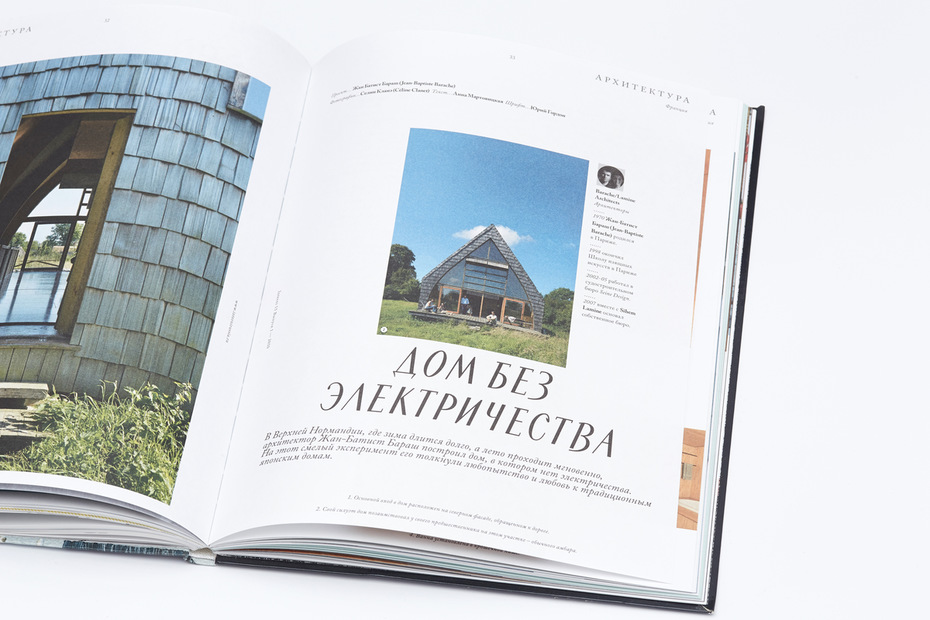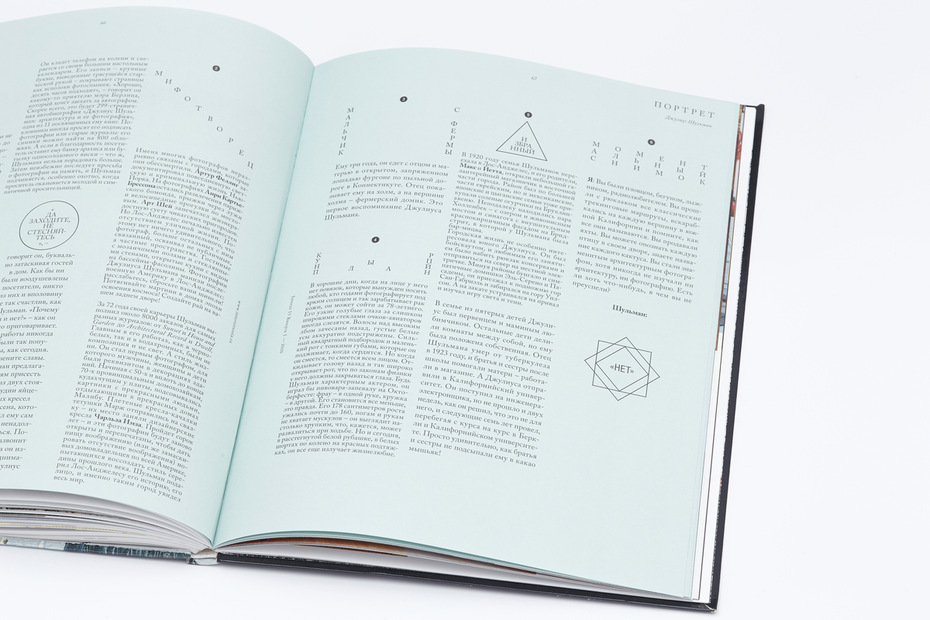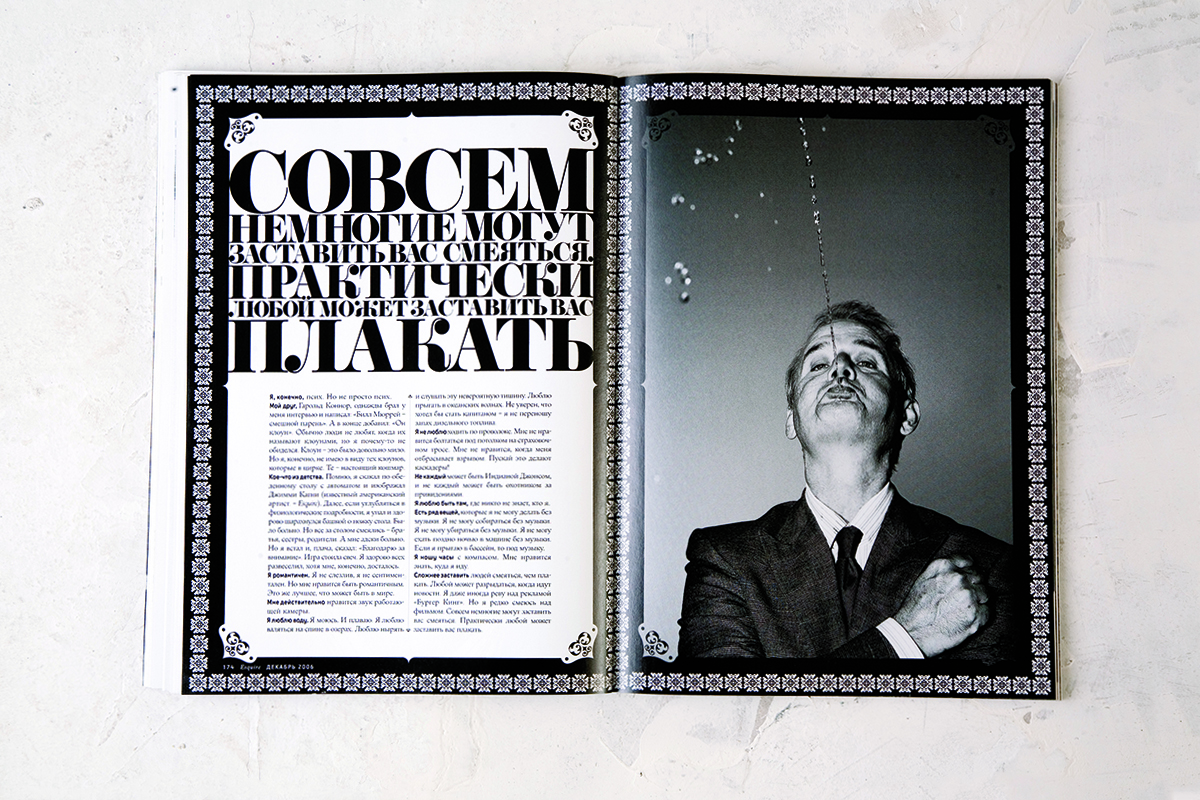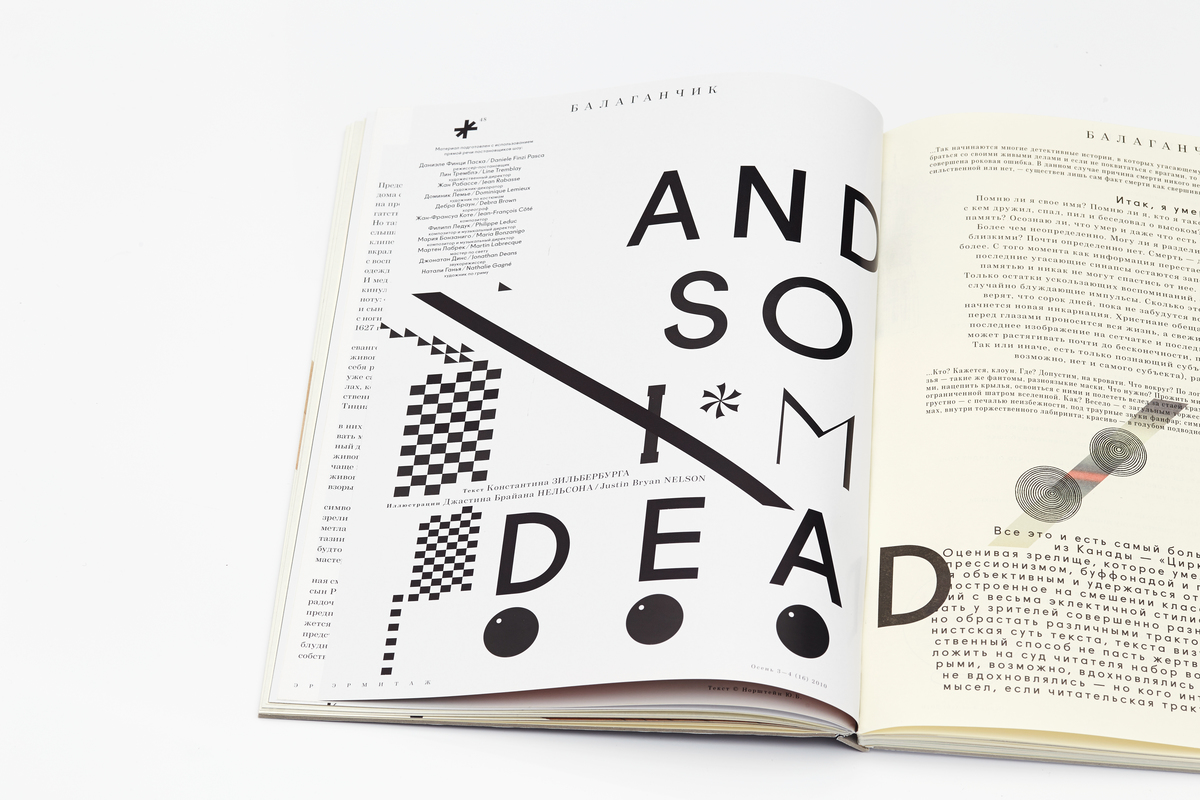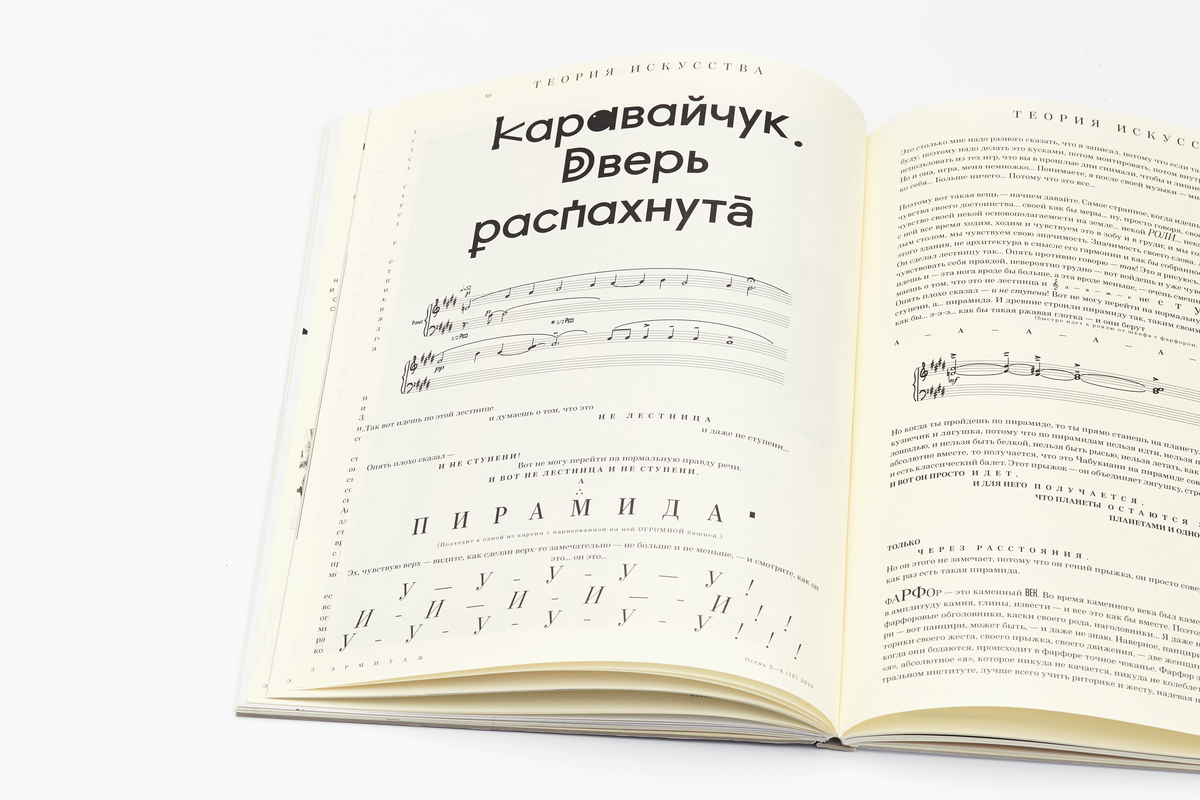
Ди­ма Бар­ба­нель на­хо­дит­ся в Со­чи на бал­ко­не квар­ти­ры, сня­той как лет­няя ре­зи­ден­ция в от­но­си­тель­ной без­опас­но­сти от COVID-19. Ев­ге­ний Юке­чев бе­се­ду­ет из рай­о­на Пан­ков в Бер­ли­не. Ди­му сле­пит май­ское солн­це, а уй­ти с бал­ко­на он не мо­жет — у Юке­че­ва есть же­ла­ние за­дать за­го­тов­лен­ные во­про­сы. Из­на­чаль­ной за­да­чей бы­ло об­су­жде­ние кон­крет­ных про­ек­тов с рас­став­ле­ни­ем по хо­ду нуж­ных ак­цен­тов, но Ди­ма ушёл в ме­та­фи­зи­ку с эле­мен­та­ми ис­по­ве­ди, при­шлось до­пи­сы­вать в два приёма. Уда­лось по­го­во­рить о сле­ду­ю­щем: как раз­ви­вал­ся ме­ди­а­ры­нок в кон­це 90-х и в 2000-е, по­че­му шриф­то­вое пи­рат­ство бы­ло не­из­беж­но­стью для ма­кет­чи­ка, как най­ти ба­ланс меж­ду за­ка­зом и вы­руч­кой и как со­брать во­круг се­бя сот­ни ди­зай­не­ров на еже­днев­ные ди­зайн-тре­ни­ров­ки.
Ди­ма, рас­ска­жи про са­мое на­ча­ло: про ли­хие 90-е, про за­пуск Esquire, про «Афи­шу» и про твои пер­вые ко­ман­ды. Ты ведь вы­рос в ре­дак­ци­ях, пер­вый опыт, на­сколь­ко я по­ни­маю, имен­но жур­наль­ный?
На­вер­ное, на­чать мож­но с «Афи­ши», она бы­ла той точ­кой, ко­гда мы, по­зна­ко­мив­шись с ­Фи­лип­пом Бах­ти­ным, ре­ши­ли ид­ти про­тив те­че­ния. Это был 2001 год, жур­нал «Боль­шой  Го­род». Мы хо­те­ли де­лать со­вер­шен­но но­вую шту­ку, ко­то­рая за­хва­ти­ла бы всё: бы­ла чи­та­е­ма, ­по­пу­ляр­на, ци­ти­ру­е­ма. Мы хо­те­ли, что­бы каж­дая со­ба­ка нас чи­та­ла! Во­об­ще, вся осталь­ная жизнь меж­ду «Афи­шей» и Esquire бы­ла ка­кой-то хал­ту­рой. К при­ме­ру, был кор­по­ра­тив­ный жур­нал, ку­да ме­ня по­звал Да­ни­ла Шо­рох, с ко­то­рым мы то­же ­ра­бо­та­ли в «­Афи­ше» и ко­то­рый пришёл из Playboy так же, как я, толь­ко на год или два поз­же. До это­го я ещё пе­ре­де­лал Playboy в на­уч­но-по­пу­ляр­ный жур­нал из до­воль­но мерз­ко­го из­да­ния о сись­ках. Это из­ба­ви­ло ме­ня от не­об­хо­ди­мо­сти еже­не­дель­но­го ка­стин­га ка­ких-то жен­щин, но при этом я дал чи­та­те­лям воз­мож­ность чи­тать тек­сты, ко­то­рые го­то­ви­ли пре­крас­ные жур­на­ли­сты: ­Ан­тон Кра­сов­ский, Эдик До­рож­кин, Лев Да­нил­кин, Серёжа Ти­тов и мно­го лю­дей, ко­то­рые оста­ви­ли след в жур­на­ли­сти­ке на­ча­ла 2000-х. Од­ним сло­вом, мы на­ча­ли про­цесс раз­ру­ше­ния Playboy как ин­сти­ту­ции и пе­ре­де­ла­ли его в ­ли­те­ра­тур­но-пуб­ли­ци­сти­че­ский дай­джест.
В 2002-м, уво­лив­шись из «Афи­ши» по­сле про­ва­ла пер­вой ите­ра­ции «Боль­шо­го Го­ро­да», мы по­шли с Да­нил­ки­ным де­лать не­мец­кий жур­нал Fit For Fun!, то­же пы­та­ясь пе­ре­де­лать его из де­биль­но­го жур­на­ла во что-то эко­ло­гич­ное.
С че­го на­ча­лась ис­то­рия Esquire в Рос­сии, что ста­ло триг­ге­ром?
В 2004-м Фи­ля [Бах­тин] по­звал ме­ня в жур­нал FHM, на ко­то­рый то­гда ку­пил ли­цен­зию из­да­тель Ми­ха­ил фон Шлип­пе. На са­мом де­ле фон Шлип­пе — это че­ло­век, ко­то­рый ока­зал на ме­ня огром­ное вли­я­ние, да­вая мне дра­го­цен­ную воз­мож­ность де­лать то, что я счи­тал нуж­ным.
Фи­ля ушёл из «Афи­ши», стал гла­варём, со­брал се­бе ко­ман­ду из мод­ни­ков и кра­са­виц. В ка­кой-то мо­мент он ме­ня по­звал на раз­го­вор вме­сте со Шлип­пе. Это был за­жи­га­тель­ный раз­го­вор. Я так, как сей­час, не умел раз­го­ва­ри­вать, я был груст­ный чу­вак, по­то­му что у ме­ня был хро­ни­че­ский га­стрит и я де­лал ве­щи, ко­то­рые мне не нра­ви­лись, и ни­ка­кие бла­га не мог­ли ском­пен­си­ро­вать это ужас­ное ду­шев­ное не­спо­кой­ствие. Раз­го­вор был о том, что «а да­вай-­ка де­лать на­ко­нец то, что мы ре­ши­ли де­лать в ­Афи­ше». То есть да­вай вме­сте сде­ла­ем офи­ген­ную шту­ку, ко­то­рую все бу­дут чи­тать. Это бы­ло на­ча­лом рус­ско­го Esquire. Если бы я ещё чуть-чуть на­хо­дил­ся в том со­сто­я­нии ду­шев­но­го упад­ка, то со мной точ­но бы что-то слу­чи­лось. За эту встре­чу, про­дол­жав­шу­ю­ся ми­нут со­рок, Фи­ля ма­стер­ски, точ­но, вы­ра­зи­тель­но, ве­се­ло сфор­му­ли­ро­вал про­грам­му на сле­ду­ю­щие пять лет. Это бы­ло очень кру­то. Я сра­зу со­гла­сил­ся.
Че­рез ка­кое-то вре­мя я при­е­хал в Independent Media, по­лу­чил там про­стран­ство для пе­ре­го­во­ров и при­ду­мы­ва­ния, и уже в де­ка­бре ­2004-го мы пе­ре­се­ли на Твер­скую в спе­ци­аль­но сня­тый для Esquire офис, и я за­нял­ся най­мом ди­зай­нер­ской ча­сти ко­ман­ды. С Esquire бы­ло всё слож­но, по­то­му что в ка­кой-то мо­мент на­ша друж­ба с Фи­лей раз­ва­ли­лась. Мы бы­ли вы­ну­жде­ны ра­бо­тать вме­сте, но бо­лее ком­форт­ная ра­бо­та бы­ла у Фи­ли с Мак­сом Ни­ка­но­ро­вым, по­то­му что Макс — мяг­кий, тон­ко чув­ству­ю­щий па­рень, не экс­тре­мист.
Мы с Фи­лип­пом хо­те­ли де­лать вы­ра­зи­тель­ные ве­щи на гра­ни до­пу­сти­мо­го, в том чис­ле и для нас са­мих, кван­то­вы­ми прыж­ка­ми пре­одо­ле­вая один свой ком­плекс за дру­гим. Од­на­ко нам обо­им бы­стро ста­ло яс­но, что при об­щей це­ли путь к ней каж­до­му из нас пред­став­лял­ся по-раз­но­му. Где-то Фи­ля был на­мно­го резвее ме­ня — воз­мож­но, я про­сто не по­спе­вал за хо­дом его мыс­ли.
В ито­ге я сде­лал 20 но­ме­ров, это где-то два го­да с хво­стом, хо­тя у ме­ня та­кое впе­чат­ле­ние, что я си­дел в Esquire це­лую веч­ность. Про­сто в ка­кой-то мо­мент ста­ло яс­но, что я сде­лал всё, что хо­тел. На но­вый язык у ме­ня не бы­ло сил, по­то­му что в это вре­мя уже бы­ли сплош­ные скан­да­лы. Фи­ля ушёл из жур­на­ла в 2011-м.
Вы на­ча­ли ра­бо­тать с Юрой Гор­до­ном как раз в Esquire, вер­но? Я по­мню ти­по­гра­фи­че­ские фо­ку­сы в каж­дом но­ме­ре. Это бы­ло, ка­жет­ся, са­мым яр­ким из все­го на рын­ке. Как вы сра­бо­та­лись?
Зна­ешь, я ис­пы­ты­ваю к Юре аб­со­лют­ный пи­е­тет. Мне нра­вит­ся, что он не клас­си­че­ский шриф­то­вик. И я мог с ним раз­го­ва­ри­вать про ве­щи от­влечён­ные, бри­фуя его так же, как я это де­лал со все­ми ху­дож­ни­ка­ми, ил­лю­стра­то­ра­ми, фо­то­гра­фа­ми и т. д. В си­лу соб­ствен­но­го нео­фит­ства я не мог ска­зать: «Про­пор­ции та­кие, за­сеч­ка та­кая, ком­пен­са­ции толь­ко здесь и здесь». Это поз­же я уже смог бри­фо­вать до­ста­точ­но де­таль­но, по­ни­мая осо­бен­но­сти шриф­та. То­гда я ни­че­го про это не знал, мне ну­жен был об­раз. Юра не вда­вал­ся в глу­би­ны про­ек­ти­ро­ва­ния шриф­та, де­лая по­верх­ност­но, но это ме­ня пол­но­стью устра­и­ва­ло. По­то­му что я то­же де­лал сти­ли­сти­че­ское ме­си­во и не стре­мил­ся ни к ка­ко­му вы­хо­ло­щен­но­му чи­сто­плюй­ству — и был по­это­му по­ри­ца­ем все­ми, кем толь­ко мож­но.
Юра — пре­крас­ный ин­стру­мент, он де­лал ров­но то, что нам тре­бо­ва­лось, его луч­шие ре­ли­зы — это всё рав­но ка­кая-то кол­ла­бо­ра­ция, Мак­са с ним или моя с ним.
С са­мо­го на­ча­ла у нас бы­ли шриф­ты из аме­ри­кан­ско­го ма­ке­та — Village и Diadema Фре­де­ри­ка Гау­ди, мы их толь­ко ки­рил­ли­зо­ва­ли, и ещё не­сколь­ко кре­тин­ских шриф­тов ка­ко­го-то гол­ланд­ца, ко­то­рый сде­лал очень стран­ный гро­теск. Мы оста­ви­ли их шриф­ты на пер­вое вре­мя — хо­тя по­том вы­яс­ни­лось, что по ли­цен­зии это­го не тре­бо­ва­лось, но пол­но­стью пе­ре­де­ла­ли весь ма­кет, ни­че­го не взяв из аме­ри­кан­ско­го жур­на­ла, кро­ме ча­сти шриф­тов, на­зва­ния и ло­го­ти­па.
Жур­нал «Эс­квайр», № 5. Глав­ный ре­дак­тор: Фи­липп Бах­тин; арт-ди­рек­тор: Ди­ма Бар­ба­нель.
Фо­то: Ма­ри­ан­на Ро­зен­стил. Ок­тябрь, 2005.
Как «Эс­квайр» по­ле­тел?
Это про­изо­шло уже в на­ча­ле 2005-го. Четвёр­тый но­мер Esquire был для нас всех клю­че­вой, пе­ре­лом­ный. Это тот са­мый но­мер, на об­лож­ке ­ко­то­ро­го Джон Мал­ко­вич с прон­зи­тель­ным взгля­дом. Кста­ти, ма­ло кто за­ме­тил, что в углу гла­за у Мал­ко­ви­ча сле­за . Мы сра­зу по­ня­ли, что де­ло по­шло, ко­гда нам ста­ли да­вать ре­кла­му. Если три пер­вых но­ме­ра мы жи­ли как бы в кре­дит, то даль­ше по­шли про­да­жи, и про­да­жи, нуж­но при­знать, при­лич­ные и да­же уди­ви­тель­ные. Ко­неч­но, это нас очень ра­до­ва­ло. По­хо­же, то, что мы с Фи­лей об­су­жда­ли в 2001 го­ду на бал­ко­не, замёрз­ши­ми паль­ца­ми ки­дая снеж­ки на кры­шу ре­сто­ра­на «Пуш­кин» и на подъ­ез­жа­ю­щие ли­му­зи­ны, ста­ло ре­аль­но­стью. ­Не­ве­ро­ят­ное чув­ство.
Что бы­ло по­сле Esquire? Рас­ска­жешь про Interni? Это же бы­ла аб­со­лют­но эстет­ская ис­то­рия. Уди­ви­­тель­но, что он ­про­дер­жал­ся так дол­го.
Жур­нал Interni по ре­дак­тор­ской и мар­ке­тин­го­вой за­дум­ке со­сто­ял из двух ча­стей. Мы не хо­те­ли ста­вить ре­кла­му во вто­рую часть жур­на­ла прин­ци­пи­аль­но, она со­сто­я­ла сплошь из ре­дак­ци­он­но­го кон­тен­та, со­бран­но­го на мод­няц­кой рых­лой бу­ма­ге. Ита­льян­ский Interni был кон­сер­ва­ти­вен, мы за­да­ли тренд, ко­то­рый под­хва­ти­ло ещё не­сколь­ко ли­цен­зи­а­тов, а по­том и са­ми ита­льян­цы по­ме­ня­ли ма­кет на чуть бо­лее со­вре­мен­ный, а с ним и де­ле­ние на две ча­сти и раз­ные бу­ма­ги. Пер­вая часть жур­на­ла бы­ла на глян­це­вой ме­лов­ке, бе­лиз­на бы­ла не­силь­ная. Все руб­ри­ки бы­ли при­ду­ма­ны та­ким об­ра­зом, что­бы уме­щать­ся в по­ло­су или мак­си­мум в две. Ред­кол­ле­гия, со­би­рав­ша­я­ся на че­ты­ре ча­са раз в не­де­лю, да­ва­ла воз­мож­ность всей ко­ман­де пол­но­стью уви­деть про­дукт и по­том в те­че­ние двух не­дель про­из­вод­ства за­ни­мать­ся лишь до­строй­кой, тю­нин­гом. В эти че­ты­ре ча­са всё при­ду­мы­ва­лось с вы­со­чай­шей кон­цен­тра­ци­ей вни­ма­ния и очень точ­ным спар­рин­гом меж­ду участ­ни­ка­ми. Веб толь­ко-толь­ко на­чи­нал­ся, и мы как бы иг­ра­ли в не­го на бу­ма­ге.
Вто­рая часть бы­ла рых­лая и очень сво­бод­ная в пла­не воз­ду­ха, мы ком­по­но­ва­ли как хо­те­ли. Пер­вая ите­ра­ция ма­ке­та (2007 – 2009) бы­ла без сквоз­ной сет­ки. Ко­гда я за­ни­мал­ся пе­ре­дел­кой Harper’s Bazaar, мне уда­лось про­ме­рить но­ме­ра 60-х го­дов из ар­хи­вов Хёр­ста , и я по­нял, что ста­ри­ки-ма­кет­чи­ки ис­поль­зо­ва­ли ка­кую-то сквоз­ную си­сте­му, ко­то­рую я дол­го ис­кал. Я хо­тел най­ти ре­ше­ние — и нашёл. Я на­звал этот спо­соб сквоз­ной сет­кой и на­чал его сра­зу же при­ме­нять.
До Esquire, в Playboy, я ду­мал, что всё стро­ит­ся на це­лых чис­лах, что мне нуж­но всё счи­тать в мет­ри­че­ских чис­лах. Ко­гда же я стал де­лать ма­ке­ты толь­ко в пунк­тах, то со­кра­тил по­греш­ность сра­зу очень силь­но. Всё на­ча­ло схо­дить­ся иде­аль­но, я кай­фо­вал от ощу­ще­ния, что по­ми­мо класс­ных ре­ше­ний у нас класс­ные тек­сты ино­гда и класс­ные кар­тин­ки. Луч­шие ав­то­ры хо­тят с на­ми ра­бо­тать. При этом, если кто-ли­бо придёт и ска­жет: «Так, что это за ха­ос?», я его в по­ро­шок со­тру. Я мо­гу на­гляд­но до­ка­зать, что в стра­не так ни­кто не де­ла­ет. Это бы­ло до­стиг­ну­то про­сто ко­ли­че­ством ча­сов. Я обыч­ный че­ло­век. В моём слу­чае вы­иг­ры­ва­ют хо­ро­ши­сты, а не ге­нии: они ко­вы­ря­ют, ко­вы­ря­ют и на­хо­дят. И я нашёл кое-что, что даёт мне по­ни­ма­ние па­ра­мет­рии и про­пор­ци­о­ни­ро­ва­ния, ме­то­дов ком­по­зи­ции. Interni — пер­вый жур­нал, ко­то­рый был сде­лан тех­но­ло­ги­че­ски ­ка­че­ствен­но.
По­го­во­рим о прак­ти­ке вза­и­мо­дей­ствия вну­три ди­зайн-ко­ман­ды? Как те­бе удаёт­ся во­вле­кать в ра­бо­ту и точ­ным об­ра­зом на­стра­и­вать участ­ни­ков про­цес­са?
У ме­ня есть пред­став­ле­ние о не­ко­ей иде­аль­ной ра­бо­чей мо­де­ли. Это имен­но мо­дель, поз­во­ля­ю­щая пра­виль­но по­до­бран­ным лю­дям с пра­виль­ны­ми ком­пе­тен­ци­я­ми, до­кру­чен­ны­ми в ре­зуль­та­те сов­мест­ной ра­бо­ты, на ред­кол­ле­гии иметь силь­ную и точ­ную со­на­строй­ку меж­ду участ­ни­ка­ми. Со­на­строй­ка поз­во­ля­ла до­стичь глу­бин­ных, до слёз, ин­сай­тов, ко­то­рые ка­са­лись точ­но­сти, бли­зо­сти об­ра­за и смыс­ла, их сты­ков­ки. Меж­ду ре­дак­то­ром и ди­зай­не­ром про­ис­хо­ди­ло глу­бин­ное ду­хов­ное со­при­кос­но­ве­ние, со­еди­не­ние в еди­ную це­лост­ную ра­бо­чую еди­ни­цу.
Даль­ше очень важ­ную роль иг­ра­ет бриф. Моя ме­то­ди­ка со­став­ле­ния бри­фа поз­во­ля­ет вы­бран­но­му че­ло­ве­ку, ис­хо­дя из по­ни­ма­ния мной его точ­ки стар­та, его про­фес­си­о­наль­но­го и ду­хов­но­го век­то­ра, пред­ло­жить имен­но то, что даст ему мас­шта­би­ро­вать­ся че­рез мою при­клад­ную за­да­чу. Я опи­ра­юсь на глу­бо­кое зна­ние че­ло­ве­ка и его ги­по­те­ти­че­ских воз­мож­но­стей, ко­то­рые при опре­делён­ных, очень чёт­ко сфор­му­ли­ро­ван­ных усло­ви­ях да­дут ему ре­а­ли­зо­вать­ся и рас­крыть­ся.
Ре­а­ли­за­ция по­тен­ци­а­ла — это во­об­ще са­мая важ­ная шту­ка, поз­во­ля­ю­щая де­лать не­обык­но­вен­ные ве­щи и очень бы­стро да­ю­щая рост лю­дям, ко­то­рые за­ча­стую не по­ни­ма­ют и не зна­ют, но бес­со­зна­тель­но жа­ждут соб­ствен­но­го раз­ви­тия. Они ищут, они му­ча­ют­ся из-за не­вы­ска­зан­но­сти, и ты им даёшь то, что при­но­сит им мг­но­вен­ный, ча­сто очень бо­лез­нен­ный, но не­обык­но­вен­ный рост.
Я до­пус­каю: то, что они сде­ла­ют, бу­дет не тем, что я хо­тел и про­сил, со­вер­шен­но дру­гим. Но я мо­гу это адап­ти­ро­вать. Вся осталь­ная моя си­сте­ма — ма­кет, ти­по­гра­фи­ка, струк­ту­ра свя­зей — она управ­ля­е­ма, я мо­гу её под­стро­ить так, что­бы эти ве­щи — жи­вые, жиз­нен­ные, ис­крен­ние и точ­ные — при­ня­ли но­вое ре­ше­ние. Я го­во­рю: «Это офи­ген­но! Не со­всем то, но это кру­то. Я сде­лаю свою часть по-дру­го­му, хо­па!»
Ты по­стро­ил Campus  для ди­зай­не­ров на тер­ри­то­рии сво­е­го до­ма и за­пу­стил тре­ни­ров­ки Designworkout. Что даёт это те­бе в дол­го­сроч­ной пер­спек­ти­ве?
Это во­об­ще чу­до. Уди­ви­тель­но, что это про­изо­шло и ста­ло ре­аль­но­стью. Без «Ян­дек­са» и без Ильи Се­га­ло­ви­ча ни­че­го бы не по­лу­чи­лось. Он по­че­му-то по­ве­рил в нас и про­фи­нан­си­ро­вал стро­и­тель­ство и пер­вые два го­да ра­бо­ты. Сту­ден­ты там за­ни­ма­лись аб­со­лют­но бес­плат­но, про­жи­вая в Кам­пу­се по пять не­дель, имея воз­мож­ность за­ни­мать­ся с уди­ви­тель­ны­ми, очень та­лантли­вы­ми ма­сте­ра­ми.
Се­го­дня прин­цип от­бо­ра на вор­ка­ут до­воль­но жёст­кий. Сю­да по­па­да­ют те, кто при­сы­ла­ет ра­бо­ту во­вре­мя каж­дый день, де­ла­ет её вы­ра­зи­тель­но и очень ка­че­ствен­но. Да­же пя­ти­ми­нут­ная по­да­ча долж­на быть сде­ла­на фан­та­сти­че­ски ка­че­ствен­но. Если че­ло­век не по­ни­ма­ет эту ме­ру ка­че­ства, то на­учить его ск­ла­ды­вать руч­ки по ро­сту и ка­ран­да­ши по мяг­ко­сти, иметь чи­стую кла­ви­а­ту­ру и вы­ров­нен­ную стоп­ку бу­маг не­воз­мож­но — это куль­ту­ра вза­и­мо­дей­ствия с про­стран­ством.
Я вы­би­раю тех, кто не про­сто го­рит или дёр­га­ет ме­ня за ру­кав, а тех, кто бу­дет си­деть пять но­чей под­ряд, всё рав­но сде­ла­ет гов­но, но бу­дет си­деть и ка­кая-то ис­кра у не­го прой­дёт. Я уви­жу, где она! Это один из сот­ни или ты­ся­чи, но они при­хо­дят, и сла­ва бо­гу.
Прак­ти­ка у Бар­ба­не­ля для мно­гих ди­зай­не­ров по­слу­жи­ла силь­ным толч­ком к про­фес­си­о­наль­но­му раз­ви­тию. Как ты это­го до­би­ва­ешь­ся?
Я ду­маю, де­ло в са­мом фор­ма­те мен­тор­ства, или пе­сто­ва­ния, мне нра­вит­ся это ста­ро­рус­ское сло­во. Это сло­во скры­ва­ет один из клю­че­вых фрейм­вор­ков для вза­и­мо­дей­ствия в ко­ман­де, тех­ни­ка на­зы­ва­ет­ся «дед». Она по­хо­жа на от­но­ше­ния двух лю­дей — стар­ше­го и млад­ше­го,— по­стро­ен­ные на ­до­ве­рии.
У от­ца, как пра­ви­ло, нет вре­ме­ни на де­тей, увы. Де­ды же своё от­ра­бо­та­ли, они име­ют ­воз­мож­ность по­свя­тить оста­ток жиз­ни вну­кам. Дед не про­сто жу­чит вну­ка, как это де­ла­ет отец по при­чи­не от­сут­ствия вре­ме­ни. Отец, вме­сто то­го что­бы по­го­во­рить с сы­ном сер­деч­но, в су­е­те осу­жда­ет его за ка­кую-то глу­пость (не вы­мыл го­ло­ву, порвал крос­си­ки, по­те­рял но­вый мяч). Для де­да это чушь, он да­же не за­ме­ча­ет это­го. Де­ду важ­но слы­шать вну­ка, ви­деть но­вую жизнь и по­ни­мать, что он и внук — это ча­сти од­ной ли­нии, точ­ка А и точ­ка Б.
Дед — это тот, кто не бу­дет го­во­рить ни­че­го су­про­тив, ни­как ком­мен­ти­ро­вать и осу­ждать, он лю­бит без­услов­но (если это хо­ро­ший дед), поз­во­ляя вну­ку рас­крыть всю кра­со­ту его сущ­но­сти. Я ск­ло­нен ис­поль­зо­вать эту тех­но­ло­гию для ре­бят. Я ни­где это осо­бо не афи­ши­рую, но я ­по­ни­маю, что это даёт им воз­мож­ность быть спо­кой­ны­ми, что у них за спи­ной есть друг, ко­то­рый их не осу­дит и все­гда под­дер­жит. Это даёт нам кре­пость.
Всё это пред­по­ла­га­ет очень силь­ную фо­ку­си­ров­ку и от­вет­ствен­ность. Для про­ек­ти­ро­ва­ния этот мо­мент — один из са­мых важ­ных. И в нём же под­пунк­том яв­ля­ет­ся не­твор­кинг — как ре­бя­та вза­и­мо­дей­ству­ют друг с дру­гом без ме­ня. Они мо­гут про­ек­ти­ро­вать что-то без ме­ня, на­стра­и­вая соб­ствен­ные рег­ла­мен­ты, и это очень хо­ро­шо.
Но всё же глав­ное для ме­ня — это, ко­неч­но, пе­ре­дать ре­бя­там по­ни­ма­ние, что нуж­но все­гда ра­бо­тать на смысл, важ­но, что­бы бы­ла це­лост­ность про­дук­та и ми­ра во­круг, про­дук­та и то­го, кто им за­ни­ма­ет­ся. Нуж­но, что­бы был слы­шен смысл! И со­вер­шен­но не тот, что со­дер­жит­ся в кли­ент­ском про­дук­те, ко­то­рый я пе­ре­де­лы­ваю, а тот са­мый Боль­шой смысл, сви­де­тель­ству­ю­щий о моём кро­шеч­ном, ми­кро­ско­пи­че­ском, му­сор­ном, без­мозг­лом уров­не, о при­сут­ствии Бо­га во­круг. Всё. Это един­ствен­ная моя цель как в про­ек­ти­ро­ва­нии, так и в мен­тор­ской прак­ти­ке.
Я мо­гу ви­деть це­лост­ность про­дук­та и пе­ре­хо­дить на слои очень бы­стро — это во­прос тре­ни­ров­ки ума. Я мо­гу ре­гу­ли­ро­вать глу­би­ну про­ник­но­ве­ния в об­раз, ско­рость, зу­ми­ро­вать, об­хо­дить, не те­ряя вни­ма­ния и на­хо­дя не­ли­ней­ные свя­зи меж­ду ком­по­нен­та­ми си­сте­мы. Ди­зай­не­ры при­хо­дят, по су­ти, ров­но за этим.
Рас­ска­жи о жур­на­ле «Эр­ми­таж». Я знаю, что это был не­про­стой про­ект. Вы­шло все­го два но­ме­ра, из ко­то­рых удач­ным ты счи­та­ешь толь­ко один. На чём ты стро­ил ма­кет, как те­бе в го­ло­ву при­шли эти ди­кие кон­струк­ции и об­ра­зы?
По­ни­ма­ешь, я ведь не ис­хо­жу из ма­те­ри­а­лов в ма­ке­ти­ро­ва­нии. Я опи­рал­ся на блю­принт, то есть на раз­вёр­ну­тое по­вест­во­ва­ние о струк­ту­ре из­да­ния, вну­трен­них смыс­ло­вых свя­зях меж­ду ком­по­нен­та­ми и о той су­пер­за­да­че, ко­то­рую эти ком­по­нен­ты в каж­дой руб­ри­ке долж­ны вы­пол­нять. Я уви­дел ор­га­низм из­да­ния, ко­то­рый пред­став­лял со­бой про­стран­ство, как буд­то ав­стра­лий­ский скрэб — ты за­хо­дишь и ви­дишь ку­чу ве­ток, эти вет­ки со­еди­не­ны. Ощу­ще­ние, что ты вошёл в очень плот­ную ней­рон­ку. У те­бя ку­ча свя­зей, и ты дол­жен их учи­ты­вать в ма­ке­те та­ким об­ра­зом, что­бы они рас­кры­лись и ин­тер­фейс жур­на­ла был по­ня­тен. UX был все­гда! Про­сто тер­мин стал по­пу­ляр­ным в по­след­ние де­сять лет, а этим все, соб­ствен­но, и за­ни­ма­лись, про­ек­ти­руя.
На про­тя­же­нии всей жиз­ни я тя­ну за од­ни и те же нит­ки. Я их про­сто вы­тя­ги­ваю даль­ше и даль­ше. Кста­ти, че­рез де­сять лет по­сле то­го, как мы сде­ла­ли шрифт для «Эр­ми­та­жа», я по­зво­нил Юре и ска­зал: «Юр, наш за­каз­чик — по­соль­ство Ир­лан­дии, да­вай этот шрифт сда­дим ир­ланд­цам, до­ба­вим ту­да раз­ной жу­ти, ко­то­рая бы иден­ти­фи­ци­ро­ва­лась ими как на­ци­о­наль­ная». На про­тя­же­нии дол­гих лет это од­ни и те же иг­ро­ки, у ко­то­рых жизнь раз­ви­ва­ет­ся бла­го­да­ря про­ек­там.
Со­дер­жа­тель­ная часть «Эр­ми­та­жа» до на­ше­го втор­же­ния в ре­дак­цию бы­ла лю­бо­пыт­ной, а для мно­гих и во­все без­ум­ной, но если коп­нуть глуб­же, на­вер­ное, мне бы­ло скуч­но­ва­то с ни­ми. Я был увлечён, ра­до­вал­ся каж­до­му но­ме­ру, но при этом со­дер­жа­тель­ная и об­раз­ная це­лост­ность впер­вые бы­ла до­стиг­ну­та толь­ко Серёжей Мо­на­хо­вым, мы его при­гла­си­ли ре­дак­то­ром на вто­рой но­мер. Это бы­ла вспыш­ка Серёги­но­го ге­ния. Мне нра­вил­ся его не­ве­ро­ят­ный без­ум­ный ум. Мы бы­ли все на сво­их ме­стах: я не лез, он не лез, мы про­сто со­труд­ни­ча­ли, ду­ма­ли, ужа­са­лись вме­сте. Это был очень глу­бо­кий про­цесс. Но на уров­не ре­ше­ний он был не та­кой кру­той, как смысл. По­ни­ма­ешь, во всех хо­ро­ших ра­бо­тах (а их очень ма­ло) все­гда глав­ную роль иг­ра­ют два об­сто­я­тель­ства, ко­то­рые обес­пе­чи­ва­ют ско­рость и вы­ра­зи­тель­ность,— это, без­услов­но, друж­ба и му­за.
В ма­ке­те «Эр­ми­та­жа» гро­теск Fugue Ра­ди­ма Пеш­ко про­зву­чал до­воль­но гром­ко и вы­шел да­ле­ко за его пре­де­лы, о нём (о вас) го­во­ри­ли мно­го и с эн­ту­зи­аз­мом. Что дал этот шрифт те­бе и ма­ке­ту?
Ма­кет уточ­нял­ся два но­ме­ра, бе­лый был пи­лот­ный, в це­лом не­удач­ный. Де­лая вто­рой но­мер, мы учли всё и сде­ла­ли со­вер­шен­но дру­гой жур­нал. Плюс Ра­дим Пеш­ко анон­си­ро­вал ки­рил­ли­цу Fugue, и не бы­ло ну­жды поль­зо­вать­ся кон­тра­факт­ной — на моём пу­ти к от­ка­зу от пи­рат­ства это бы­ло очень во­вре­мя. По­ня­тия «ма­кет» на са­мом де­ле в жур­на­ле «Эр­ми­таж» не­ту. Там нет ша­бло­нов и ком­по­но­воч­ных схем, в основ­ном про­сто раз­мер­но­сти шриф­тов и от­но­ше­ния эле­мен­тов. Сам ма­кет по­стро­ен на сквоз­ной сет­ке с ша­гом мо­ду­ля 5,834 мм, ко­то­рый яв­ля­ет­ся и меж­ко­лон­ни­ком. Внеш­ние от­сту­пы так­же под­чи­не­ны это­му мо­ду­лю, что даёт об­ра­зу ак­ту­аль­ную для 2010 го­да остро­ту. Этот но­мер там, по-мо­е­му, ни­ко­му не по­нра­вил­ся. Кро­ме Пио­тров­ско­го. Осталь­ные не до­го­ня­ют, ко­му и за­чем всё это нуж­но. Пио­тров­ский, уди­ви­тель­ный че­ло­век, под­пи­сал этот ма­кет в пе­чать. Я бы не под­пи­сал, будь я на его ме­сте.
Мне за­по­мни­лось ин­тер­вью с Оле­гом Ка­ра­вай­чу­ком из вто­ро­го но­ме­ра. Ма­кет и ти­по­гра­фи­ка уди­ви­тель­но точ­но сов­па­да­ют с экс­цен­трич­ной лич­но­стью ком­по­зи­то­ра и его по­вест­во­ва­ни­ем.
Это ве­ли­кий сю­жет! В этом ма­те­ри­а­ле Ка­ра­вай­чук сам вы­сту­пил ти­по­гра­фом, вы­де­лив в вёрст­ке не­об­хо­ди­мые по смыс­лу (и зву­ча­нию) ак­цен­ты и опре­де­лив всю ком­по­зи­цию пуб­ли­ка­ции. Но­мер вы­пус­кал­ся, ко­гда эпо­ха фан­та­зий­ных шриф­тов-ги­бри­дов бы­ла ещё при­зрач­ным бу­ду­щим. На за­ход­ной по­ло­се — по­пыт­ки до­пол­нить кас­су Fugue аль­тер­на­тив­ны­ми зна­ка­ми для под­держ­ки той ди­ко­сти, ко­то­рую Ка­ра­вай­чук устро­ил вну­три. Ва­ри­а­ции тек­сто­вых раз­ме­ров — от 6,3 до 27 пт. Ждан при­ни­мал уча­стие в раз­мет­ке и был в вос­тор­ге от про­цес­са.
Ин­тер­вью с Оле­гом Ка­ра­вай­чу­ком (1927 – 2016) из вто­ро­го но­ме­ра жур­на­ла «Эр­ми­таж».
Ждан Фи­лип­пов, ди­зай­нер, со­труд­ник «Ма­стер­ской» в 2012 – 2015 го­дах: «Ра­бо­та над этой пуб­ли­ка­ци­ей ве­лась сов­мест­но с са­мим Оле­гом. Сто­я­ла за­да­ча со­про­во­дить текст му­зы­каль­ны­ми за­ри­сов­ка­ми, и Ка­ра­вай­чук с го­тов­но­стью пре­па­ри­ро­вал текст, на­ки­ды­вал нот­ные этю­ды, жон­гли­ро­вал строч­ка­ми и вме­сте с ди­зай­не­ром при­ду­мы­вал вы­ра­зи­тель­ные ти­по­гра­фи­че­ские ре­ше­ния для всех раз­во­ро­тов».
Из по­след­них ра­бот был ма­кет жур­на­ла «Ис­кус­ство ки­но»? На­сколь­ко я по­нял, про­ект не при­ня­ли и всё ушло в стол. Вещь мог­ла по­лу­чить­ся со­вре­мен­ная и дерз­кая. Рас­ска­жи по­дроб­нее.
«Ис­кус­ство ки­но» — ле­ген­дар­ный со­вет­ский жур­нал. Он вы­хо­дит с се­ре­ди­ны 20-х го­дов. Идея пе­ре­осмыс­лить и воз­ро­дить об­раз жур­на­ла для ме­ня иде­аль­ная. Я лю­блю ра­бо­тать со старьём, вы­тас­ки­вать из не­го всю си­лу сде­лан­но­го, про­жи­то­го и пе­ре­са­жи­вать это в на­шу ре­аль­ность, в се­го­дняш­нюю зем­лю. По­ни­ма­ешь, это да­же не со­всем про ди­зайн, это про про­дол­же­ние тра­ди­ций, про со­хра­не­ние куль­ту­ры, причём той куль­ту­ры, ко­то­рая да­ла фан­та­сти­че­ские рост­ки. Мне важ­ны зёр­на, я пол­заю по пла­не­те и со­би­раю их как мо­гу. По­это­му для ма­ке­та я на­хо­дил сна­ча­ла ре­фе­рен­сы из 60-х, 70-х, жур­на­лы о ки­но, ис­кус­стве, ко­то­рые де­ла­ли ста­ри­ки.
Про­ве­дя не­боль­шое изыс­ка­ние, я незна­чи­тель­но скор­рек­ти­ро­вал вы­со­ту и ши­ри­ну, вы­сту­пая ско­рее служ­бой са­на­ции, не­же­ли пи­о­не­ром графди­зай­на. Ло­мать ни­че­го не хо­те­лось, но ка­за­лось, что нуж­но уточ­нить: по­след­няя ите­ра­ция ма­ке­та вы­гля­де­ла со­всем слу­чай­ной. Я от­ре­зал ши­ри­ну и до­ба­вил вы­со­ту, по­лу­чи­лась про­пор­ция ки­но­кад­ра — 1:1,37.
Что про­ис­хо­дит с на­бо­ром? Вы ре­ши­ли жур­нал на­брать на пе­чат­ной ма­шин­ке?
Ну по­чти. Смот­ри, в ито­ге у нас в ма­ке­те три шриф­та: Repro Dot, Repro Typewriter с «за­ли­па­ми» и про­сто обыч­ный Repro Regular для са­мо­го спо­кой­но­го на­бо­ра, все Во­вки­ны. Ком­плект в рам­ках од­ной гар­ни­ту­ры даёт не­ве­ро­ят­ное бо­гат­ство на­бо­ра, но мы остаём­ся в од­них про­пор­ци­о­наль­ных от­но­ше­ни­ях, и если го­во­рим о се­ре­бре на­бо­ра — о на­бо­ре как плот­но­сти и тек­то­ни­ке,— то эти па­ра­мет­ры у них схо­жи. Мы на­хо­дим­ся вну­три от­дель­ной шриф­то­вой эко­си­сте­мы и за неё не вы­хо­дим.
Вла­ди­мирКо­ло­мей­цев
Вла­ди­мир­­
Ко­ло­мей­цев
ди­зай­нер шриф­та
Мы при­ду­ма­ли се­бе ма­шин­ку — её на­зва­ние, че­ло­ве­ка, ко­то­рый ра­бо­та­ет с ней, пи­шет сце­на­рии и за­ри­сов­ки. Я на­чал пред­став­лять, как ка­рет­ка ра­бо­та­ет, как ли­те­ры бьют по ней, как она ре­а­ги­ру­ет на уда­ры, скри­пит ли, ле­та­ет, за­ли­па­ют ли у неё бук­вы — на­сколь­ко она це­лост­на как ме­ха­низм. Зна­ешь, ко­гда что-то ин­те­рес­ное есть в го­ло­ве, мы очень бы­стро ста­ра­ем­ся это за­пи­сать, что­бы не за­быть. Как это про­ис­хо­дит, ко­гда мы поль­зу­ем­ся пе­чат­ной ма­шин­кой? На­вер­ное, очень бы­стро, силь­но и уве­рен­но бьём. Всё это вли­я­ет на ­от­тиск, го­то­вый пе­чат­ный ма­те­ри­ал. Мы по­ня­ли, что всё это долж­но быть в шриф­те на уров­не ва­ри­а­тив­но­сти букв. Ко­гда ты пой­мал об­раз за хвост, на­чи­на­ешь его бы­стро за­пи­сы­вать — это очень гряз­ные, вби­тые в бу­ма­гу бук­вы. Вну­три это­го ма­те­ри­а­ла ­по­яв­ля­ет­ся ­силь­ней­шая виб­ра­ция. Всё дре­без­жит и ­кри­чит.
«Ис­кус­ство ки­но» — это по­пыт­ка уви­деть, что на­хо­дит­ся вну­три ки­не­ма­то­гра­фи­че­ской кух­ни. Опыт­но­му зри­те­лю-фа­на­ту очень важ­но, что­бы мы рас­ска­за­ли ис­то­рию не по­верх­ност­но. Рань­ше ма­шин­ка бы­ла пред­те­чей даль­ней­шей пуб­ли­ка­ции. В опре­делён­ную эпо­ху эта же ма­шин­ка вы­да­ва­ла ре­зуль­тат про­стым ко­пи­ро­ва­ни­ем. На этом был по­стро­ен весь сам­из­дат. И сам­из­дат как ан­та­го­нист об­ще­му ме­дий­но­му стри­му в на­шем слу­чае ка­зал­ся хо­ро­шей ме­та­фо­рой.
Hearst Corporation — из­да­тель­ский трест Хёр­ста, осно­ван­ный Уи­лья­мом Хёр­стом в 1887 го­ду. Штаб-квар­ти­ра в Нью-Йор­ке. Се­мей­ство Хёр­стов ак­тив­но участ­ву­ет в управ­ле­нии ком­па­ни­ей.
Олег Ни­ко­ла­е­вич Ка­ра­вай­чук (1927– 2016) — ком­по­зи­тор, ди­рижёр, пи­а­нист, му­зы­кант-им­про­ви­за­тор, ав­тор му­зы­ки ко мно­гим ки­но­филь­мам и спек­та­клям. Со­труд­ни­чал с та­ки­ми ре­жис­сёра­ми, как Ва­си­лий Шук­шин, Сер­гей Па­ра­джа­нов, Ки­ра Му­ра­то­ва.
Hearst Corporation — из­да­тель­ский трест Хёр­ста, осно­ван­ный Уи­лья­мом Хёр­стом в 1887 го­ду. Штаб-квар­ти­ра в Нью-Йор­ке. Се­мей­ство Хёр­стов ак­тив­но участ­ву­ет в управ­ле­нии ком­па­ни­ей.